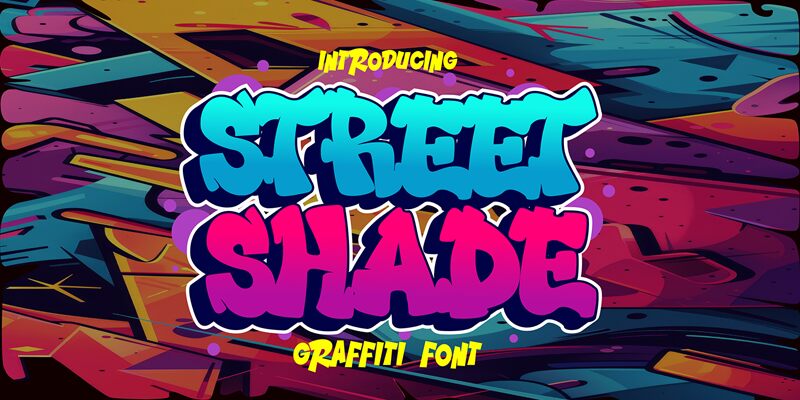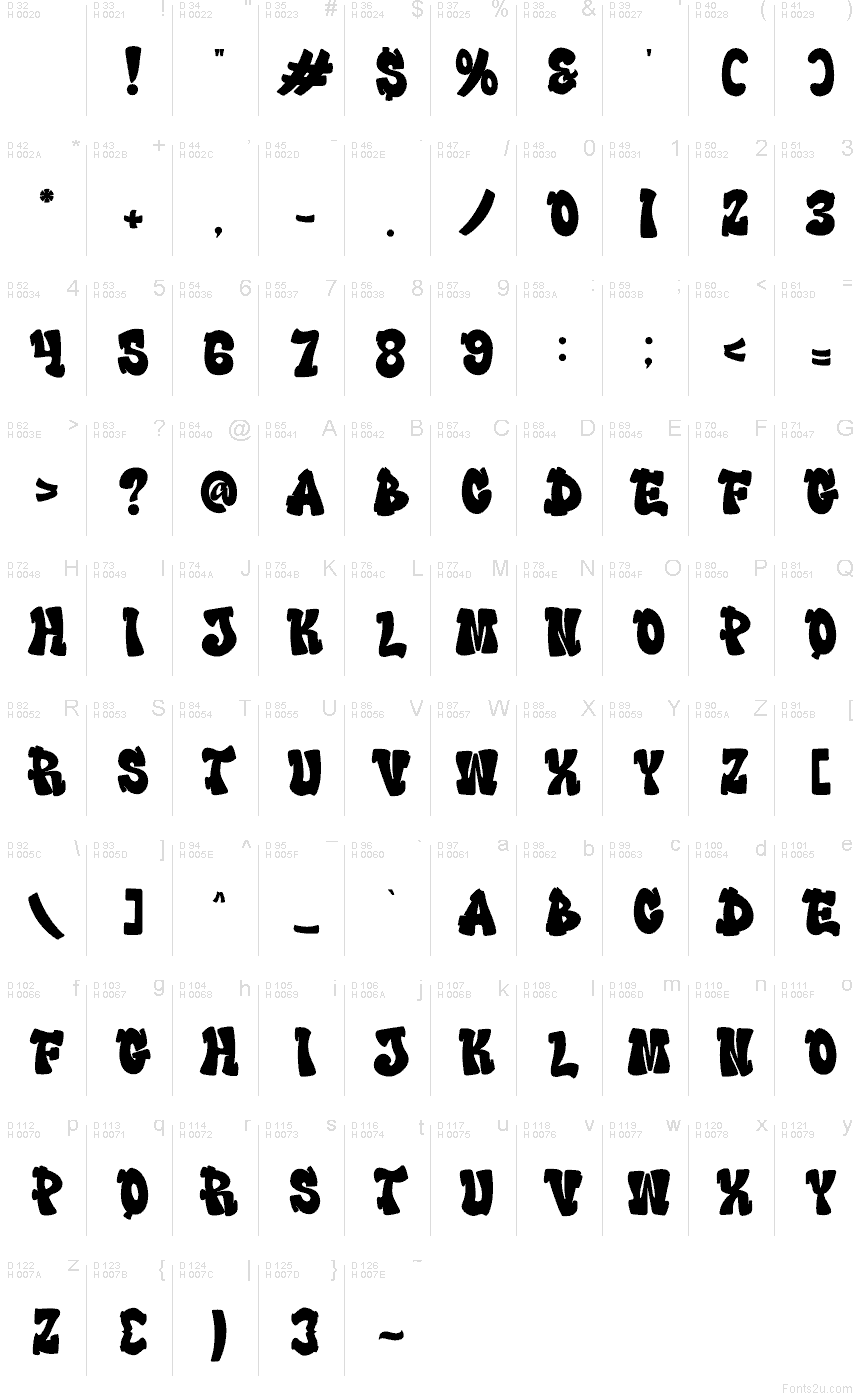
Street Shade, creata da Saepul milah di CikareotypeStudio x figureeStudio, è un font graffiti gratuito caratterizzato da forme corpose, cariche di colore e un ritmo vivace. Le lettere sembrano tracciate velocemente con lo spray: bordi irregolari, contrografie strette e quell'attitudine urbana che colpisce anche nei design più essenziali. Il peso costante dona al tuo messaggio un impatto visivo deciso, perfetto per i poster.
Con Street Shade otterrai risultati d'effetto su loghi streetwear, flyer skate e hip-hop, copertine musicali, adesivi, miniature di YouTube e post social di grande impatto. Questo font gratuito brilla anche su locandine di eventi, etichette di prodotto e titoli in stile murale dove vuoi trasmettere energia istantanea. Abbinalo a un sans serif pulito e condensato per i testi piccoli e, nei formati più grandi, aumenta leggermente il tracking per lasciare che le forme respirino.